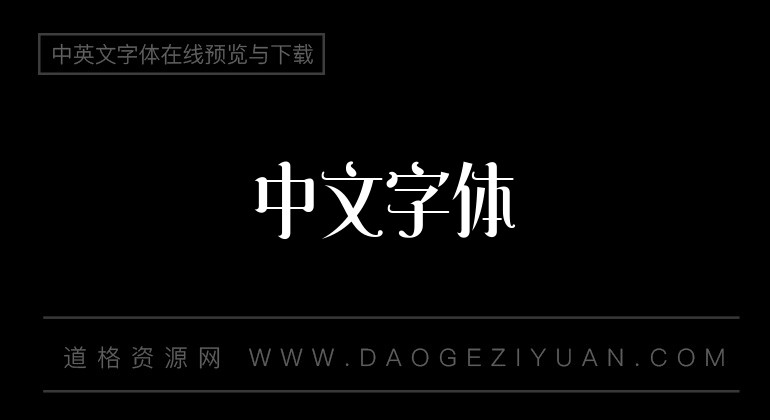
造字工房妙妙字体是一款拥有独特设计风格的中文字体,由造字工房设计师林谷雪芽创作,拥有丰富的字型结构,旨在以简洁的设计理念,为汉字文字注入新鲜的活力。字体的构成由细节到宏观,从折线到圆弧,从细节到比例,让汉字文字更加清晰,更加有趣。字体的设计风格比较平衡,结构紧凑,字形比例精确,整体美观大方,极具视觉冲击力。文件名:ZaoZiGongFangMiaoMiao-1.ttf
造字工房妙妙是一款非常不错的手写艺术字体,具有很好的视觉感,适合于文化类的宣传设计、商业类品牌的广告和产品包装设计以及个性化文字排版等较多场景。